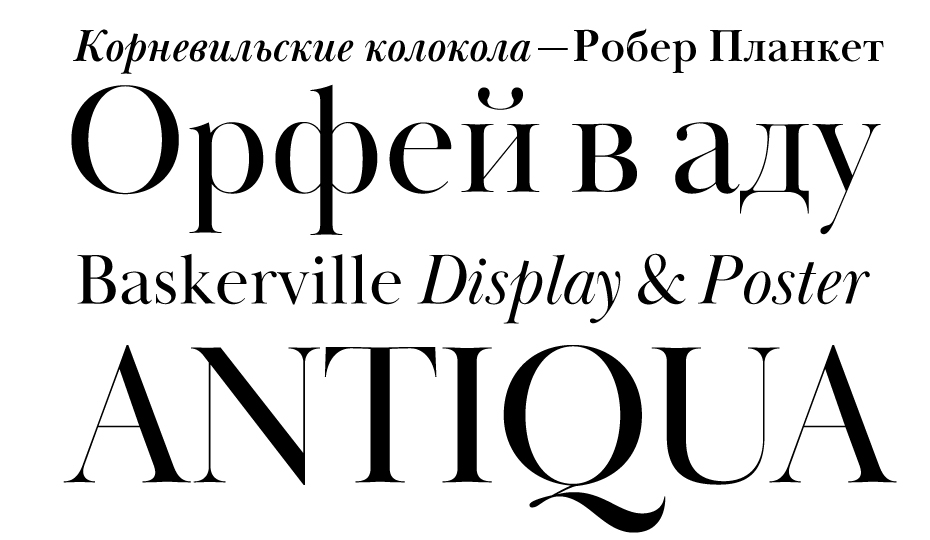
Почему бы в мае не вспомнить о прошедшем 2016 годе? Тем более что он был насыщен событиями как на глобальной, так и на локальной шрифтовой сцене. Вот некоторые из них. На конференции ATypI в Варшаве была представлена технология вариативных шрифтов, и, хотя об особенностях её применения споры не унимаются, очевидно, что отчасти будущее типографики где-то там.
Возможно, ответом на глобальный вызов Monotype (за покупкой FontShop последовало ещё два крупных приобретения: платформы визуального маркетинга Olapic и стартапа Swyft Media, зарабатывающего на эмодзи) явился Type Network — инициатива Font Bureau (Дэвид Берлоу и Роджер Блэк). В компании собран выразительный состав менеджмента и экспертного совета (в который вошли Дэвид Берлоу, Мэтью Картер, Петр ван Блокланд, Сайрус Хайсмит и другие).
Российский ландшафт тоже становится во многом интереснее: «ПараТайп» перезапустил магазин шрифтов Fonts.ru, в котором пользователям предложено сразу несколько оригинальных сценариев поиска и выбора шрифтов.
Год назад на шрифтовом рынке появился дуэт Ильи Рудермана и Юрия Остроменцкого, анонсировав свою студию CSTM Fonts и магазин type.today, — отметим впечатляющие темпы шрифтовых релизов и профессиональной активности. И наконец, многие пользователи дождались релиза новой, шестой версии шрифтового редактора FontLab.
Разобравшись с флешбеком 2016-го, вернёмся к нашему ежегодному обзору. Условия выбора проектов остались прежними: шрифт должен содержать набор кириллических знаков, право на его использование должно быть доступно для приобретения любому желающему, дата выпуска — не ранее января и не позднее декабря 2016 года. На этот раз дополнительно к десятке мы решили собрать небольшой арьергард из 9 шрифтов, а авторам шрифтов задали пару вопросов:
Итак, все 10+9 в алфавитном порядке☟
Дизайнеры: Арина Алафердова, Дмитрий Кирсанов.
Издатель: ParaType, Россия
Крупнокегельная версия шрифта Baskerville вышла в компании «ПараТайп» в сентябре 2016 года в комплектах Display и Poster. Базовые параметры гарнитур унаследованы от ITC New Baskerville, так что они составляют хорошую пару к 8 начертаниям от Джона Квартанта и Ко, сделанным в ITC в 1972 году (кириллический набор знаков был создан Тагиром Сафаевым в 1993-м). Обострённый контраст, зауженные пропорции знаков, тонкие детали (особенно примечателен курсив в Baskerville Poster) предполагают работу в крупных кеглях — и в этом масштабе Baskerville Display & Poster приобретают неприличную красоту и изящество. Можно сказать, что авторам удалось максимально претворить стремление Джона Баскервиля к тонкой и выразительной форме. Среди прописных знаков курсива можно обнаружить и альтернативные формы со свошами и росчерками, напоминающими нам о том, что сам Баскервиль был прекрасным каллиграфом.
Шрифты Baskerville и сегодня остаются рабочей лошадкой многих типографов. С советских времён (если говорить о кириллической версии) комфортные пропорции, спокойные и привычные формы этой гарнитуры встречаются на страницах детских книг, художественной литературы, документальной прозы, журналов. Эти шрифты сложно назвать остроактуальными, но они всегда будут присутствовать в арсенале дизайнера, оформляющего книгу. И теперь с появлением тщательно отрисованных крупнокегельных версий дело остаётся за умелым применением этих шрифтов не только в заголовках и на титульных страницах книг, но и в журналах, инфографике и прочих жанрах — без стеснения в кеглях и размерах.
Дизайнеры: Ольга Панькова, Илья Рудерман. Издатель: type.today, Россия
Этот неогуманистический гротеск с беспрецедентным для текстового шрифта количеством лигатур (как в латинице, так и в кириллице) был разработан по заказу журнала «Большой город». В интервью с Ильёй Рудерманом мы уже рассказывали о роли этого шрифта в издании: «Гротеск Big City сделал немало и для литературного, и для гражданского образа журнала. Во многом этому способствовала актуальная типографика с долей самоиронии, что в целом отвечало и духу индивидуальности личности, и демократизму, которые провозглашал БГ». На тот момент гарнитура содержала 11 начертаний (9 прямых и два курсивных). В 2009 году Big City стал победителем международного конкурса Современная кириллица. Шрифт долгое время оставался в эксклюзивном использовании редакцией журнала, затем начался долгий процесс доработки гротеска с участием Ольги Паньковой для публичного релиза под лейблом
В 2016 году шрифт был представлен в девяти насыщенностях (от Hairline до Heavy) с соответствующими курсивами (всего 18 начертаний). В новой версии уточнён рисунок знаков, добавлена капитель, новые лигатуры и неалфавитные символы. Если принимать во внимание, что гарнитура поддерживает более 100 языков, а лигатуры присутствуют не только в строчных, но и в прописных знаках и в капители, то грубый арифметический подсчёт даёт более 2000 лигатур в одном начертании. Умножая на общее количество насыщенностей, мы получаем астрономический объём работы, которая была проделана для того, чтобы выпустить шрифт в продажу.
Типографический потенциал этого гротеска выглядит весьма впечатляющим. Кроме необъятного количества лигатур он оснащён символами, чувствительными к регистру, всеми видами цифр, числительными, дробями, индексами, математическими знаками ключевых валют.
Стимулом к работе послужила моя стажировка в CSTM Fonts, и я была счастлива, что Илья и Юра (Илья Рудерман и Юрий Остроменцкий.
— Прим. ред.) доверили мне именно этот шрифт. Во-первых, я фанат одноимённого журнала и до сих пор храню много номеров, а во-вторых, после долгой работы над Пулитцером было очень интересно поработать с гротеском, и особенно с лигатурной частью. Поначалу страшнее всего было вносить даже минимальные изменения в контуры, ведь этим шрифтом долго набирали журнал и он прекрасно работал! Но поскольку я всё делала под чётким руководством Ильи, больших сложностей не возникало. Думаю, всё, чему я научилась в процессе создания такой большой семьи, можно считать достижениями.
08. Banaue
Banaue — это рукописный бесплатный шрифт, созданный вручную Иевой Мезуле в деревенском стиле с филиппинскими нотами.